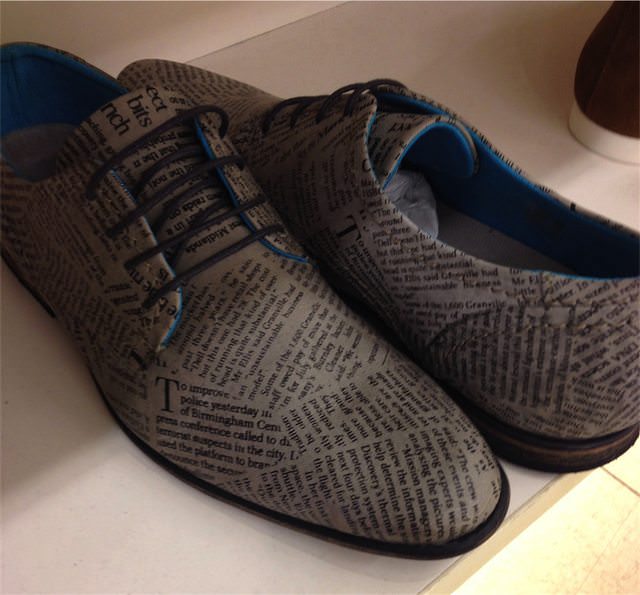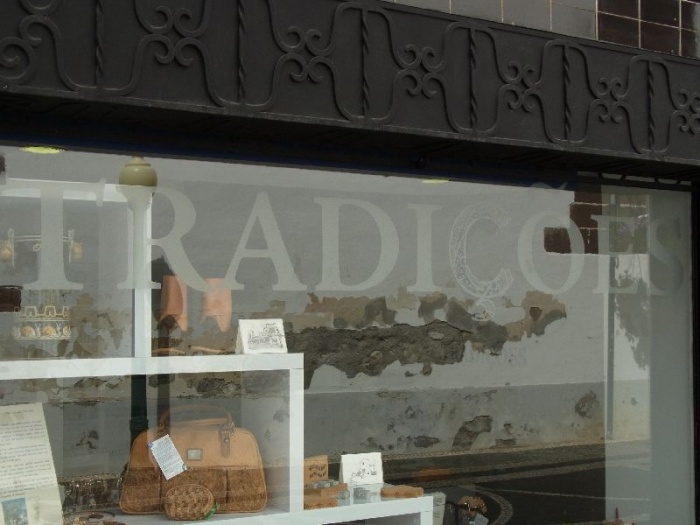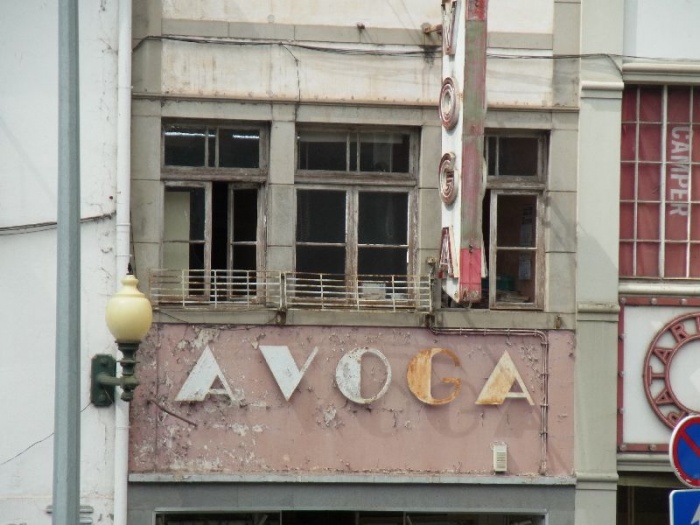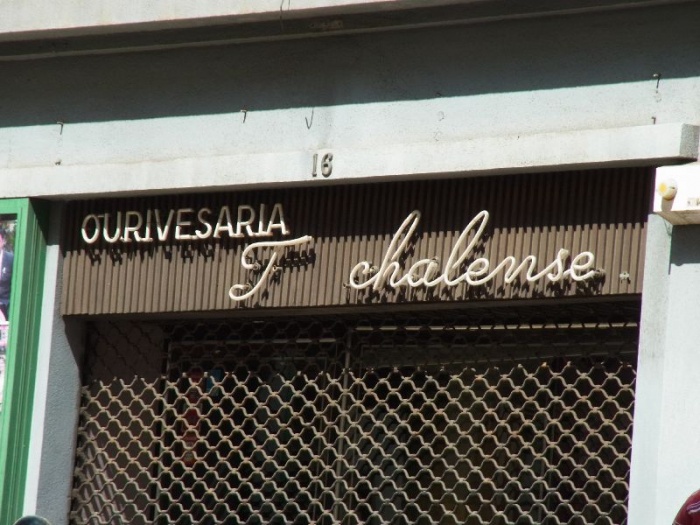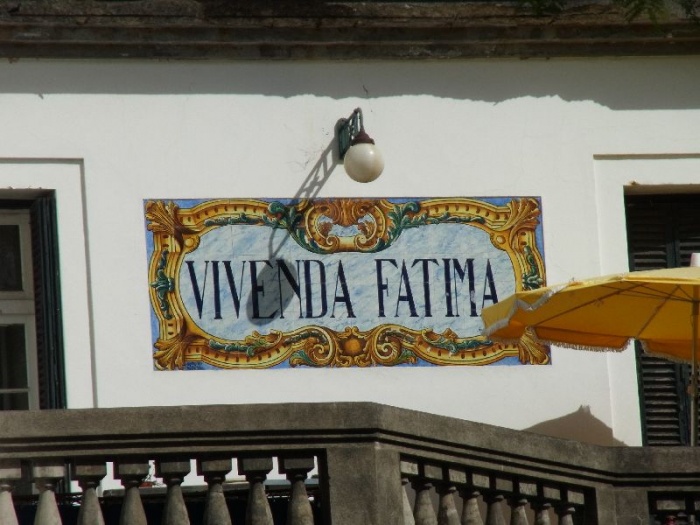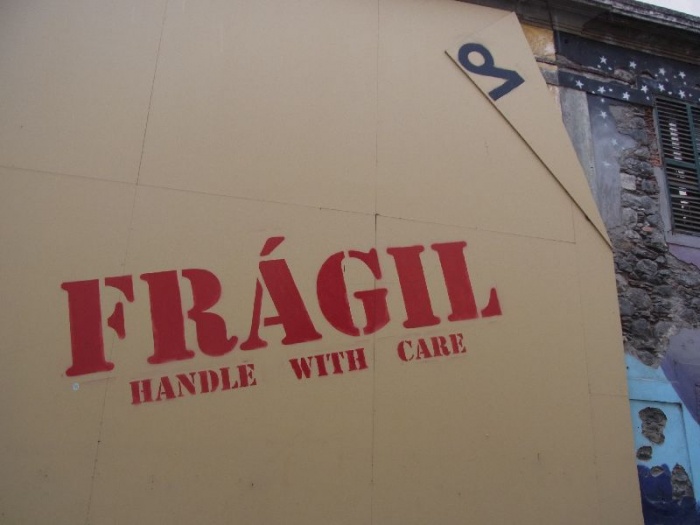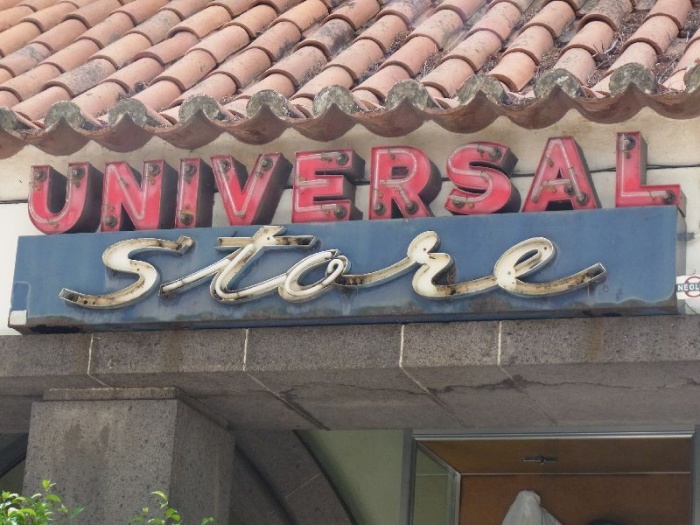
Typostreifzug durch die Stadt ...
Lilienstrasse
Wer ist denn Herr Lilien, nachdem diese Trasse benannt wurde? ;-)
Man sollte das korrekt nach Schreibung aussprechen. Für solche Fälle ist es von Vorteil, dass das ſ so selten wurde ;-)
wie wäre es mal wieder mit ein paar Bildfundstücken stadttypografischer Art? Schließlich sind wir doch hier bei den Typostreifzügen …  :!:
Einige Fundstücke von der wunderschönen Insel Madeira:
Mistral mit Outline, okay, aber ...
Ist das »Dionysos« frei gezeichnet oder gibt es eine Satzschrift mit diesem Duktus?
... da möchte man doch sofort einen Ouzo bestellen und Syrtaki tanzen.
… und zwar mit Dolch im Gewande. ;-)
Ist das »Dionysos« frei gezeichnet oder gibt es eine Satzschrift mit diesem Duktus?
Es gibt einen Freefont namens "Xmas Terpiece Regular" der so aussieht
Ich wäre nie auf die Idee gekommen, die für einen Griechen zu benutzen, aber ausgerechnet das Wort Dionysos funktioniert in dem Kontext irgendwie. Und der Reisende hat den Eindruck: Der Laden hat sich mit diesem Design schon seit den Fünfzigern gehalten, also kann er nicht ganz schlecht sein.
Ich hab’ nen paar Tage Amsterdam-Urlaub hinter mir und euch dabei natürlich nicht vergessen ;-)
Neuhaus/Oste